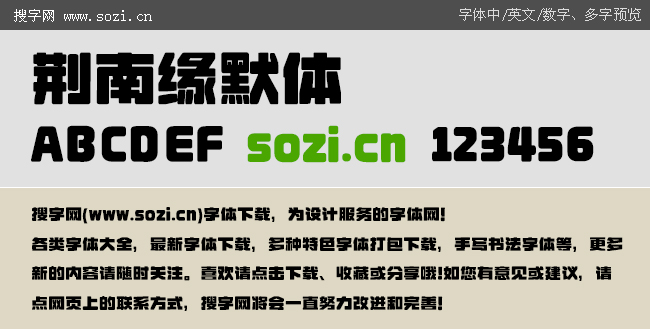
荊南緣默體
搜字網(wǎng)給大家提供一款荊南緣默體中文字體下載,該字體的字框偏扁,重心偏低。在盡可能保持字形辨識度的情況下,筆畫盡可能的粗,字盡可能占滿一個方格。筆畫過多的字某些筆畫做了特殊粗細對比處理。。適用于平面宣傳設(shè)計、網(wǎng)頁設(shè)計、海報設(shè)計等應(yīng)用。